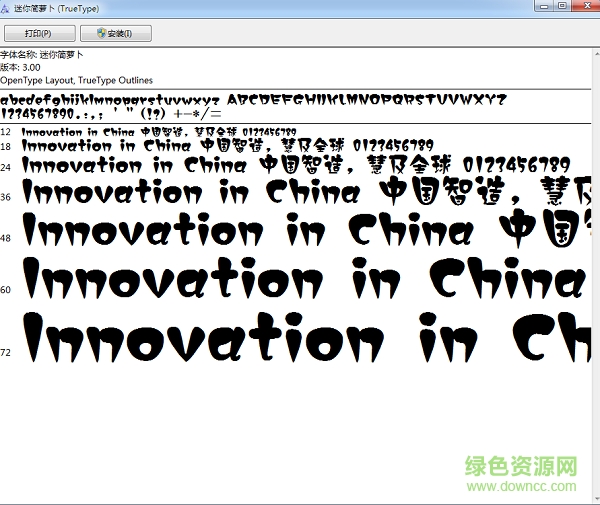
迷你簡蘿卜是一款非常有趣的電腦字體,該字體上粗下細,字形大方得體,整體效果十分出色,并且字庫完整,非常適合需要用到藝術(shù)字體的朋友,喜歡可以來綠色資源網(wǎng)下載!
迷你簡蘿卜是以蘿卜為原形而設(shè)計的一款簡體中文漢字,可以適用于名片設(shè)計、平面設(shè)計、廣告設(shè)計、報紙雜志、企業(yè)LOGO、商標(biāo)注冊、電視臺廣告等領(lǐng)域